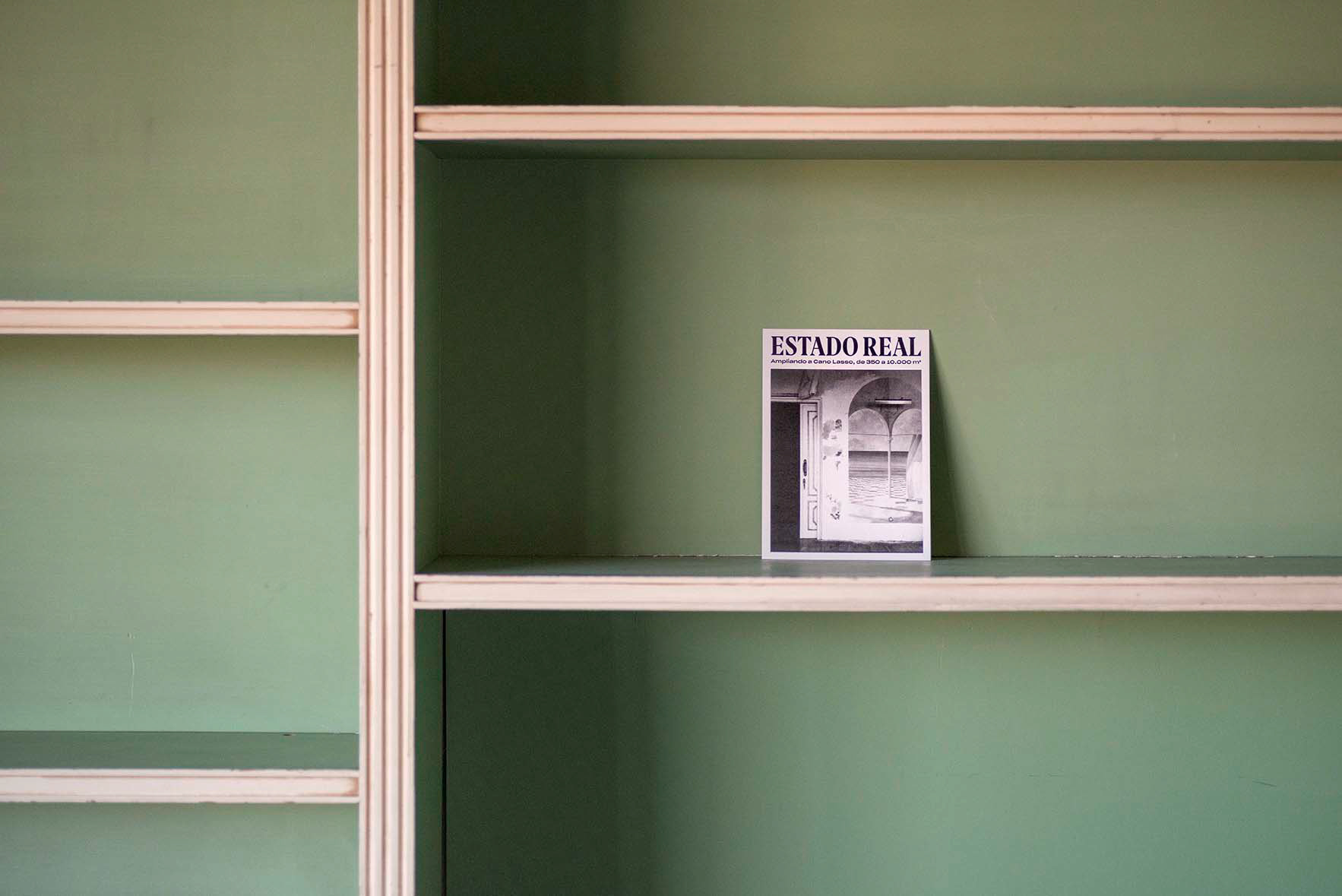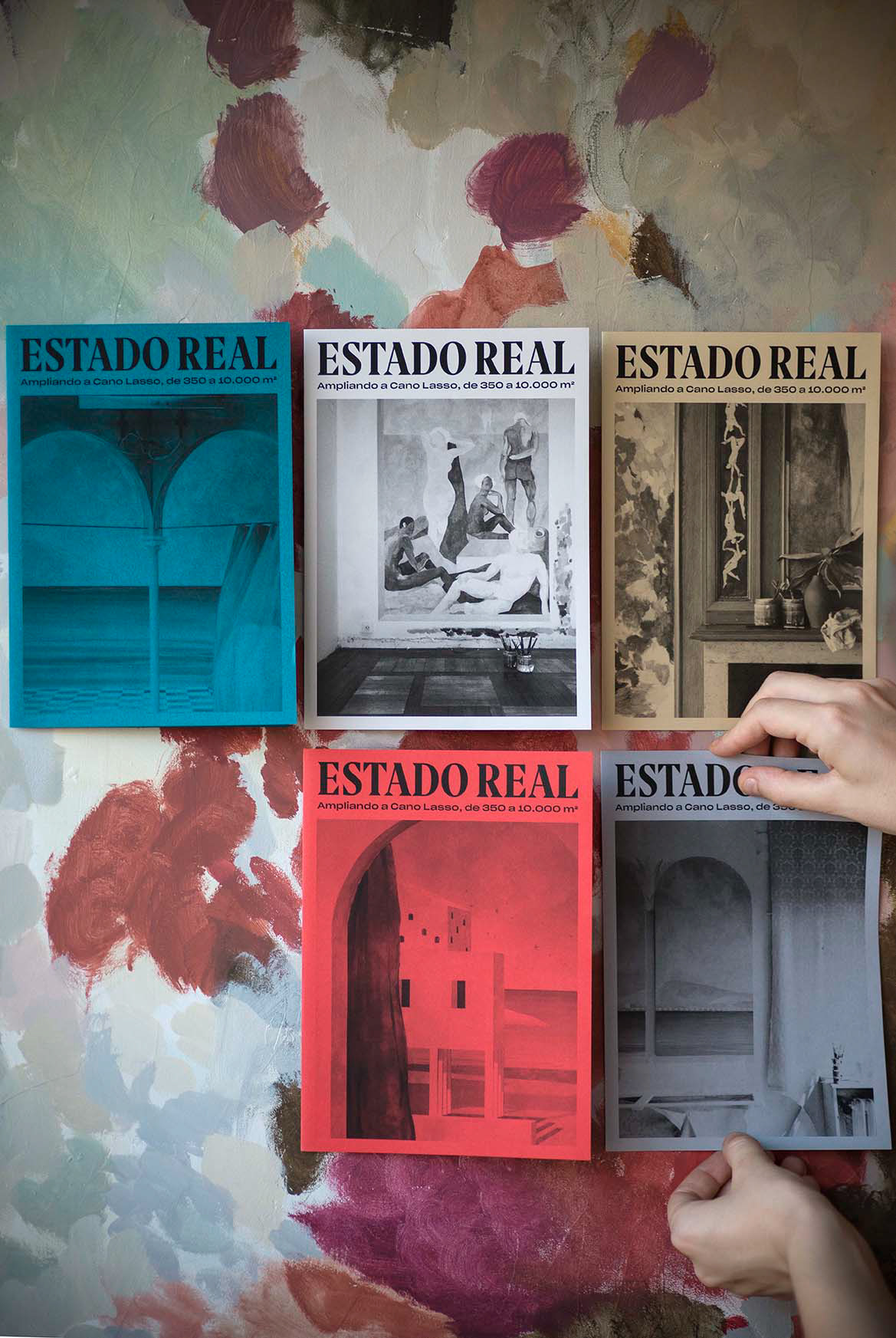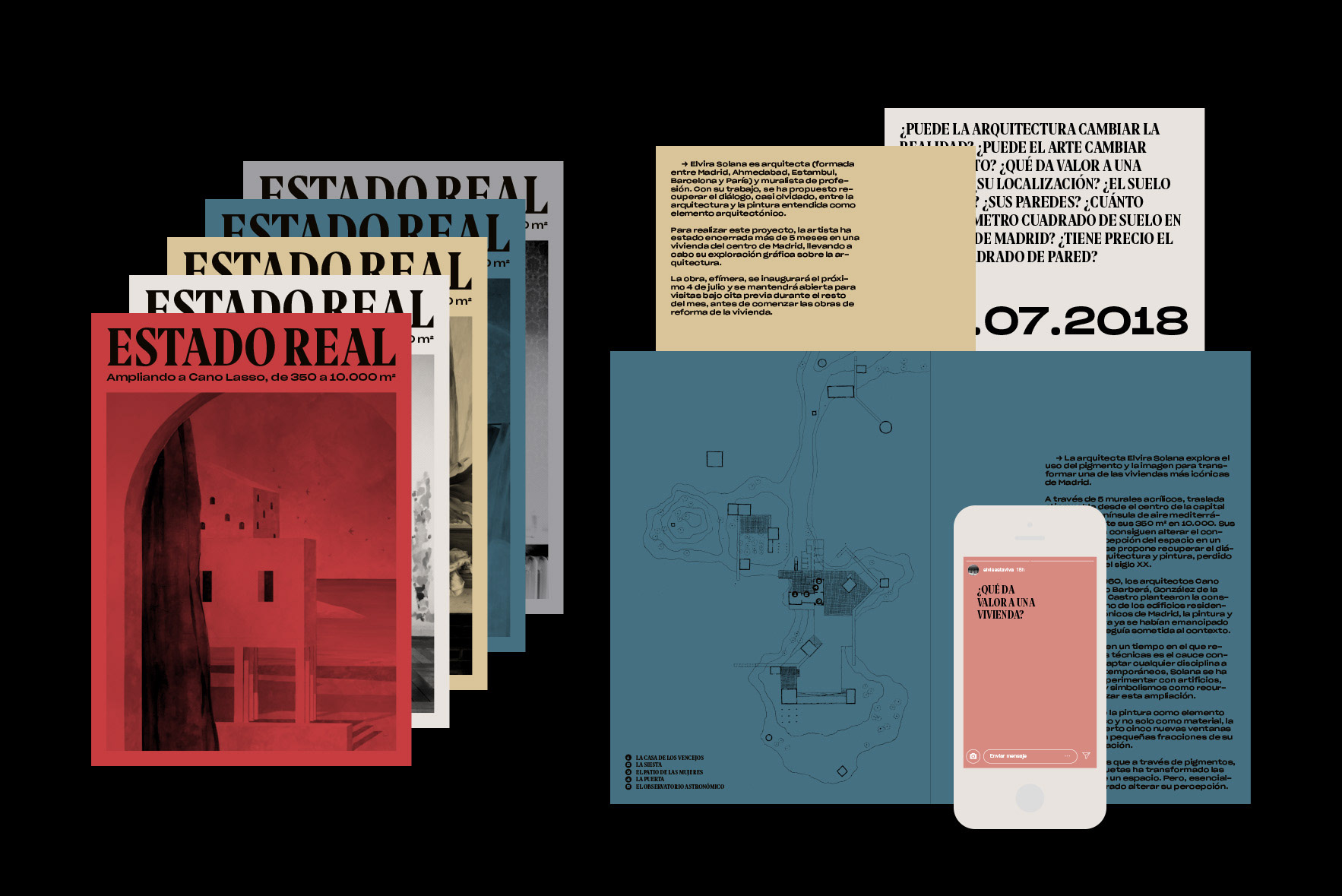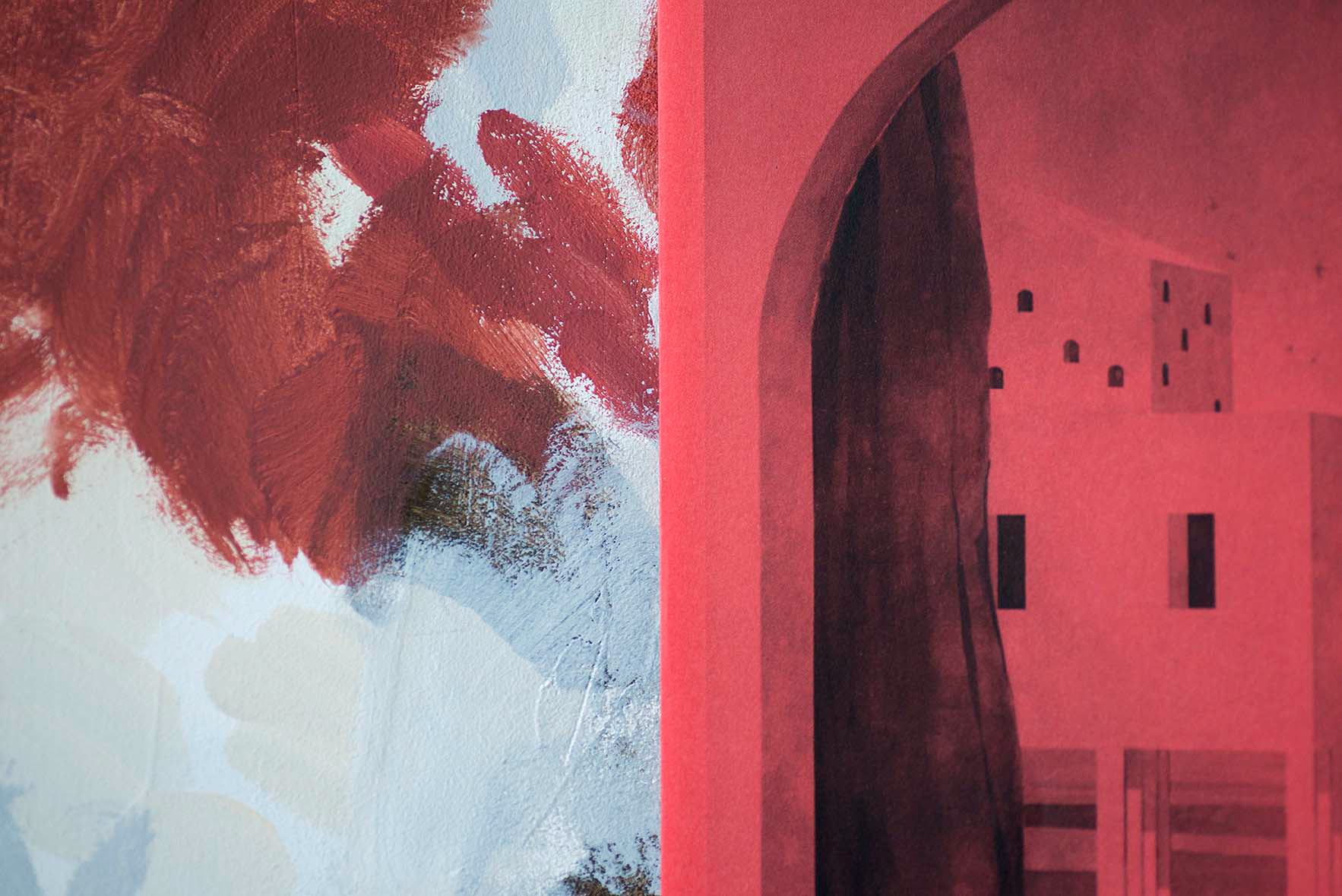
Identidad gráfica para el proyecto artístico “ESTADO REAL. Ampliando a Cano Lasso, de 350 a 10.000m2”, de la arquitecta y muralista Elvira Solana.
La imagen de la exposición efímera ESTADO REAL tuvo como fin generar expectación en torno a la intervención artística de la arquitecta y muralista Elvira Solana, así como la producción de una serie de piezas impresas tales como cartelería, invitaciones y hojas de sala explicativas. La obra consistía en la deslocalización de una vivienda de lujo de Madrid a partir de una serie de murales pintados en su paredes, que mostraban las vistas de su nuevo emplazamiento costero y ficticio.
Con el objetivo de potenciar el diálogo entre pintura y arquitectura planteado, se eligieron dos tipografías complementarias que representaban el tradicional mundo pictórico y el universo técnico de vanguardia, respectivamente. La paleta de papeles de color se escogió a partir de los pigmentos utilizados en los murales. Las invitaciones incluían una pieza de tela resultante del proceso de destape de las paredes de la casa, anteriormente forradas.
Graphic identity for the art project “ESTADO REAL. Ampliando a Cano Lasso, de 350 a 10.000m2”, exhibition of the architect and painter Elvira Solana.
The image of the ephemeral exhibition ESTADO REAL was intended to generate expectation around the artistic intervention of the architect and muralist Elvira Solana, as well as the production of a series of printed pieces such as posters, invitations and explanatory room sheets. The work consisted in the relocation of a luxury home in Madrid from a series of murals painted on its walls, which showed the views of its new seaside and fictional site.
With the aim of enhancing the dialogue between painting and architecture, I chose two complementary typographies that represented the traditional pictorial world and the avant-garde technical universe, respectively. The palette of colored papers represent the pigments used in the murals. The invitations included a piece of cloth resulting from the process of uncovering the walls of the house, previously covered.